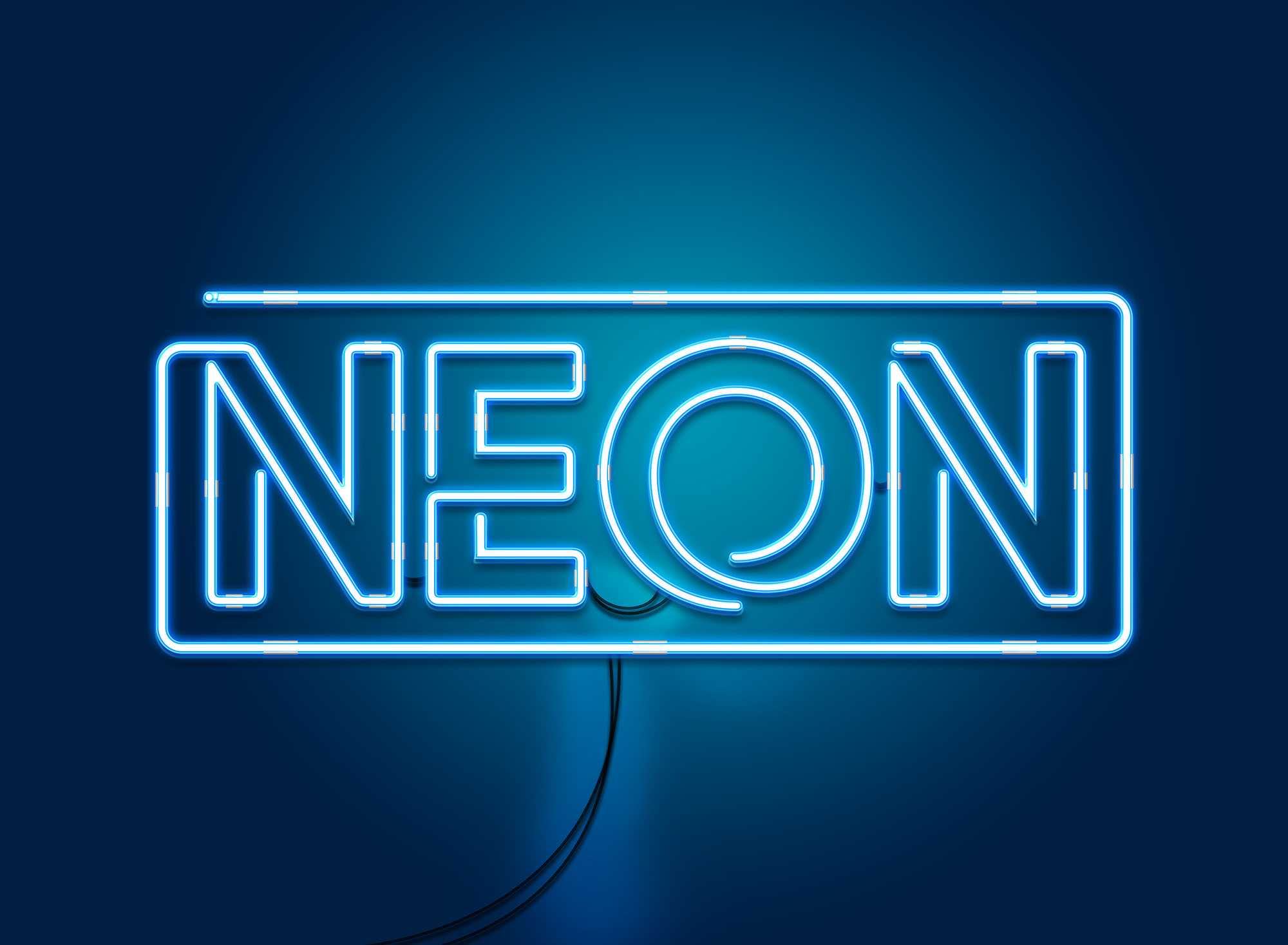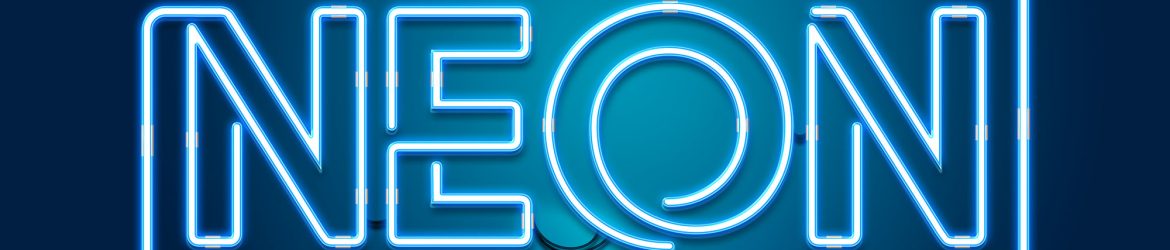
Neon Free Font é uma tipografia feita sob a ideia de neon, em estilo de linha contínua. Isto permite que trabalhe perfeitamente em signagens neon, mas também se adapta a várias aplicações de design, de marcas a embalagens. Esta fonte de neon também é perfeitamente adequada para banners em linha, onde o ‘brilho’ pode alternar para chamar a atenção do usuário. Para tornar o efeito ainda mais imponente, você pode usar alguns mockups gratuitos para criar um efeito de ‘glifos’, como mostrado nas imagens de pré-viés. Mesmo sem precisar de um download direto da fonte, você encontrará um mockup de neon que você pode usar aqui.